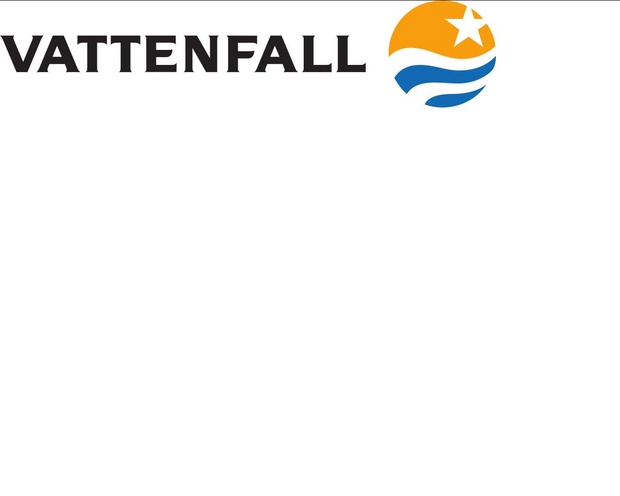
Welches ist die Vattenfallschrift?
Also, ich vermute mal, dass die Interstate und die OCR-B die Unternehmensschriften sind, die für Schriftverkehr und Unternehmenskommunikation bei Vattenfall eingesetzt werden. In sehr vielen Fällen ist das Logo eines Unternehmens aber nicht aus der gleichen Schrift gesetzt wie die Unternehmenstexte, um es deutlich von diesen abzusetzen und seine formale Eigenständigkeit nicht zu schwächen.
Es ist – wie Stefan auch schreibt – aber sehr wahrscheinlich, dass das keine normale Satzschrift ist, sondern eine Satzschriftmodifikation, die durch den Logodesigner stattgefunden hat.
Da könnte die
Pate gestanden haben.